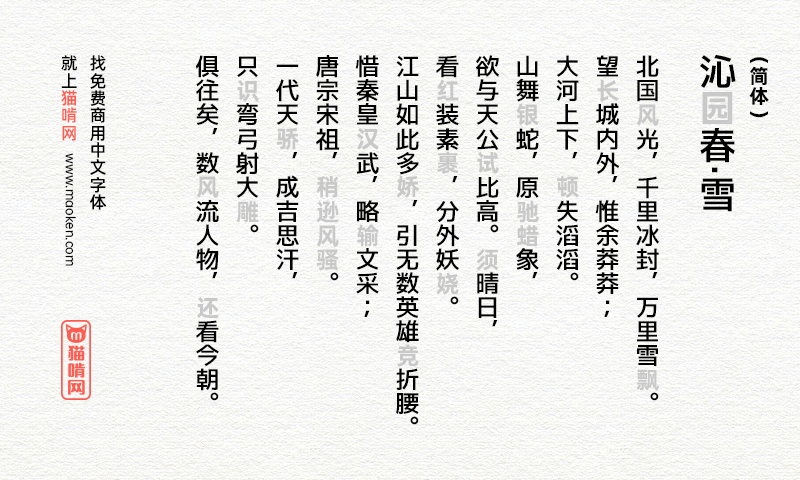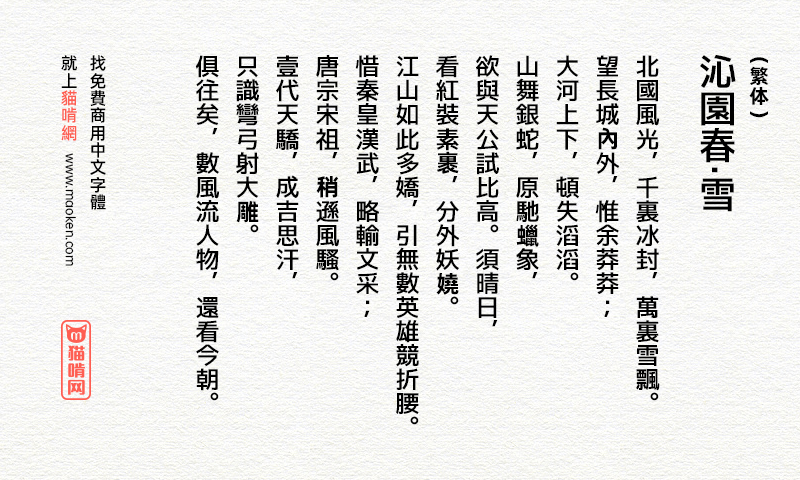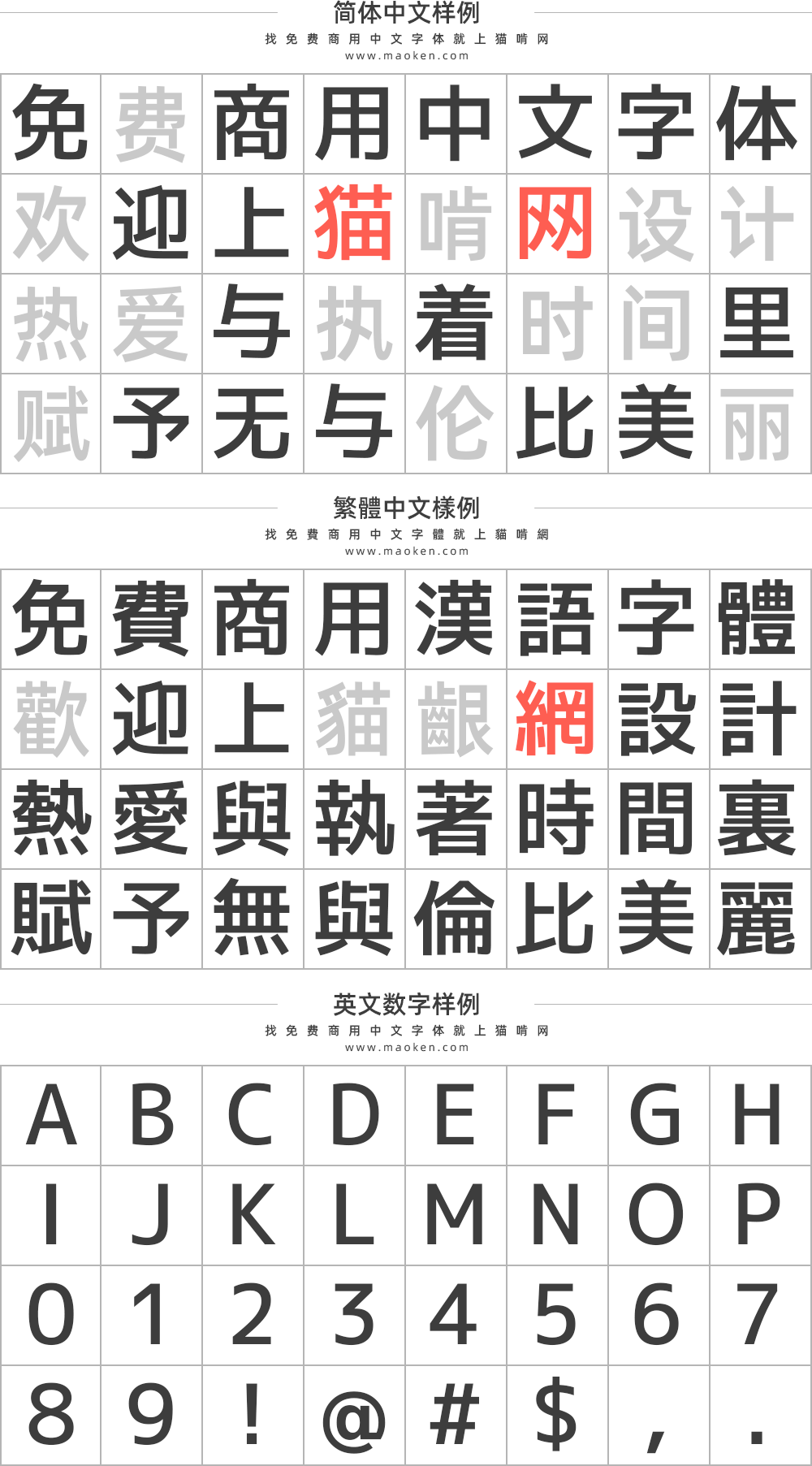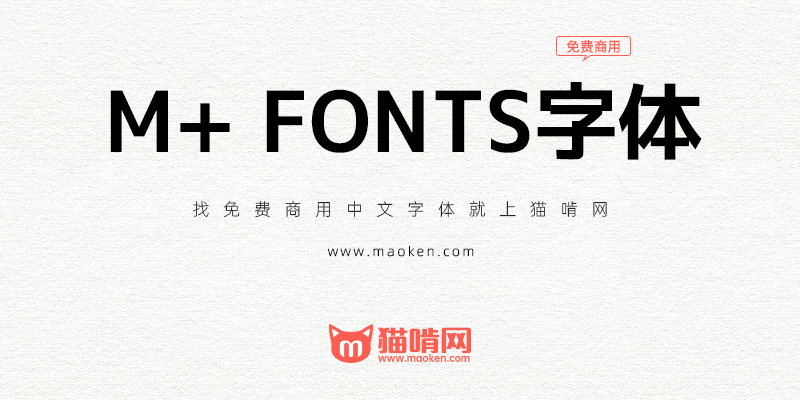
M+ FONTS:有爱的独特而丰富的日系免费商用黑体字型
M+FONTS发布于2003年,至今已经历18年。而今,M+FONTS发布M+2版本,并新增了可变字形,并把字体以OFL授权释出。M+FONTS已经将其开发环境迁移到GitHub。OSDN上没有新的更新。旧的信息和字体文件可以在下面的“OSDN”链接中找到,但也请参阅新的“GitHub”版本。
在谷歌的支持下正在修改字体设计。现在,GF Latin Plus欧文文字组等文字组合了以前的汉字,Mplus1和Mplus2,并且Mplus code字体暂定公开中。新的文字设计也显示在现在看到的这个字体上。
这个字体是老常客了,RPG Maker的默认字体就是这个,玩RPG游戏时经常能看到
M+ 這個字體繁體缺字太多 連「關」這種常用字都沒收錄 建議給兩星
• 日语用「関」比较多